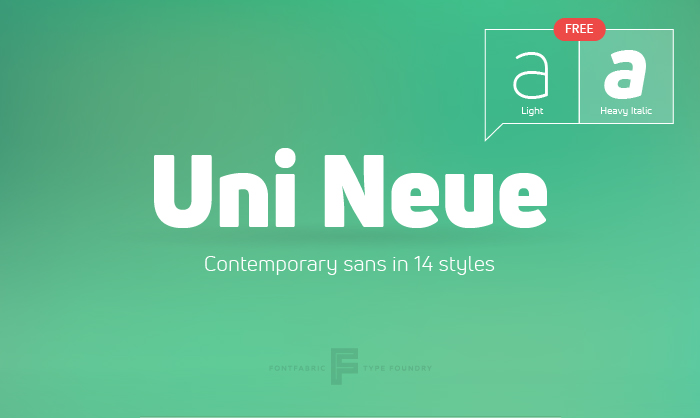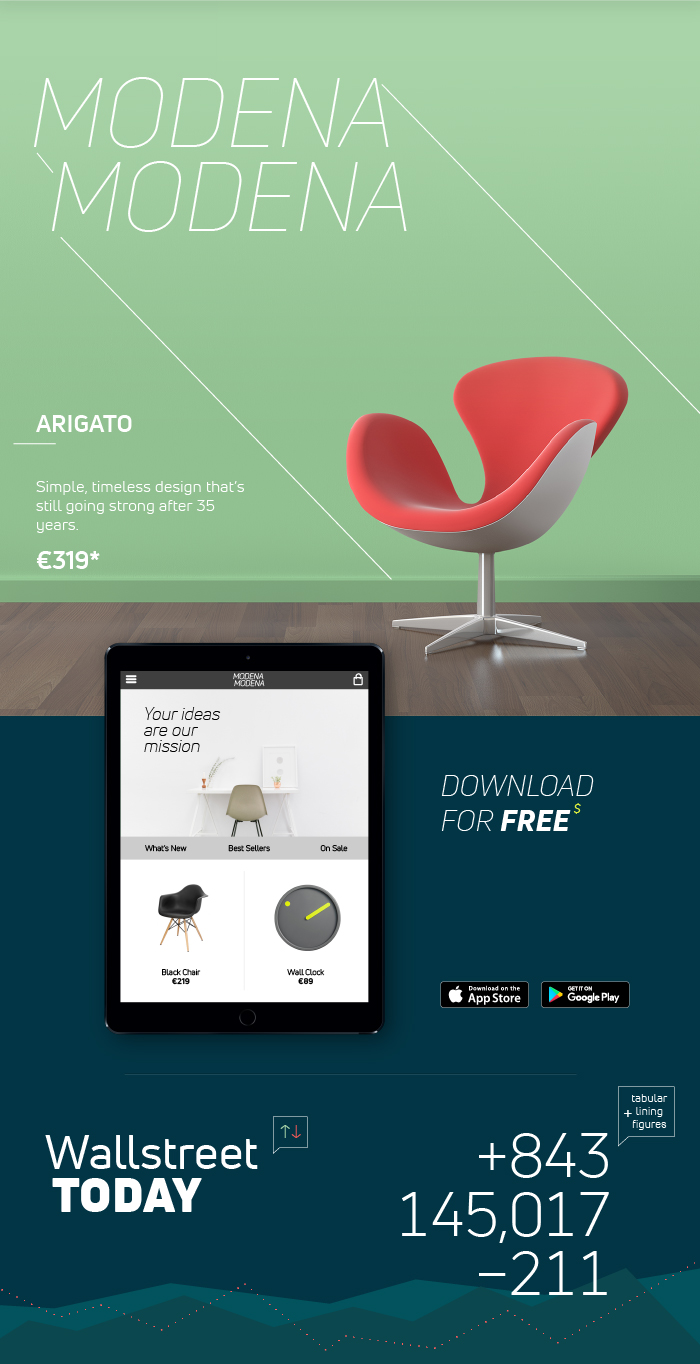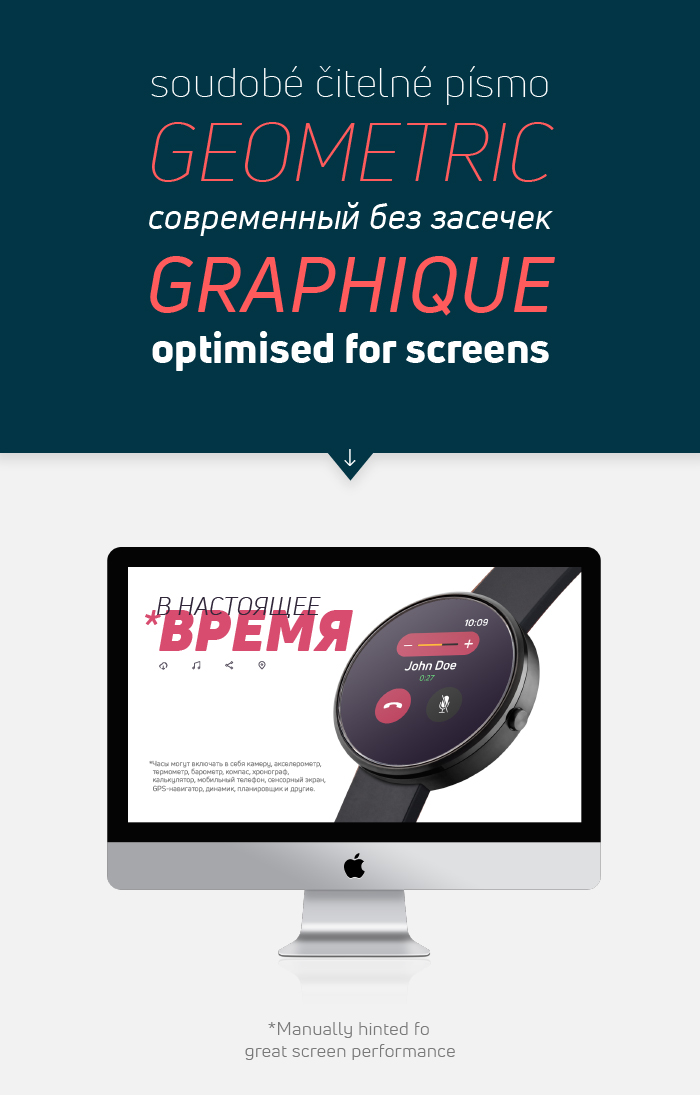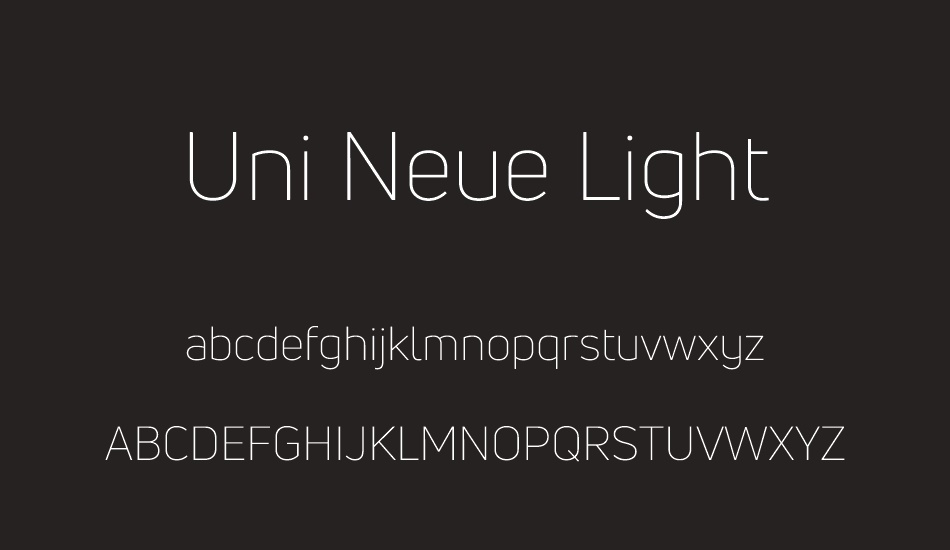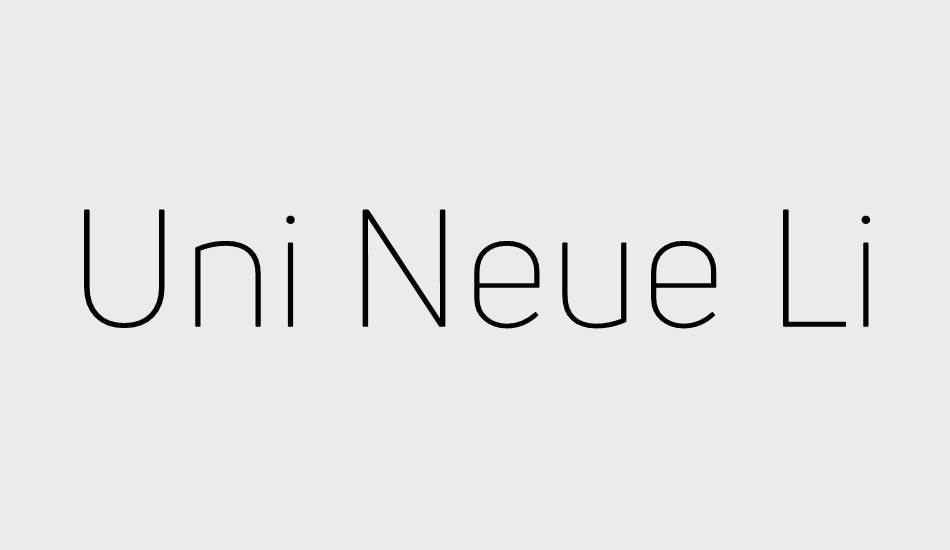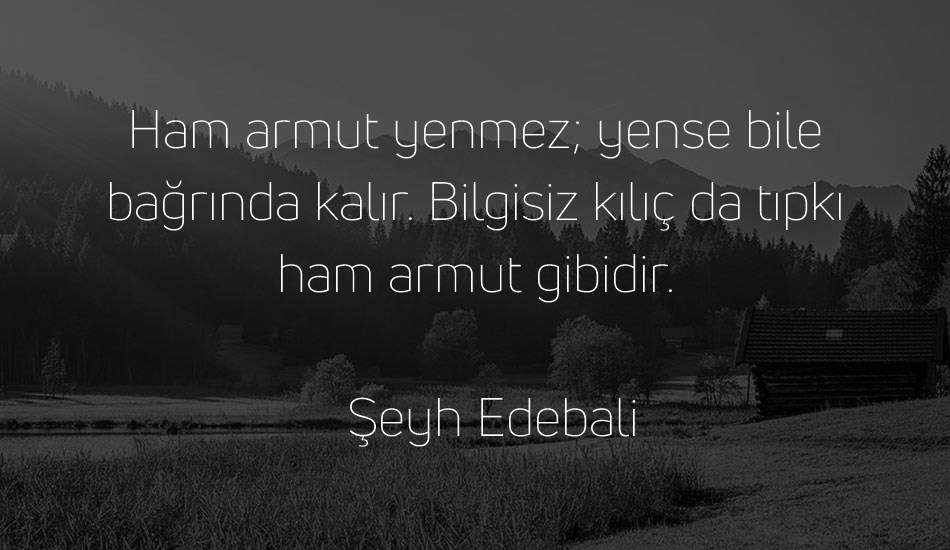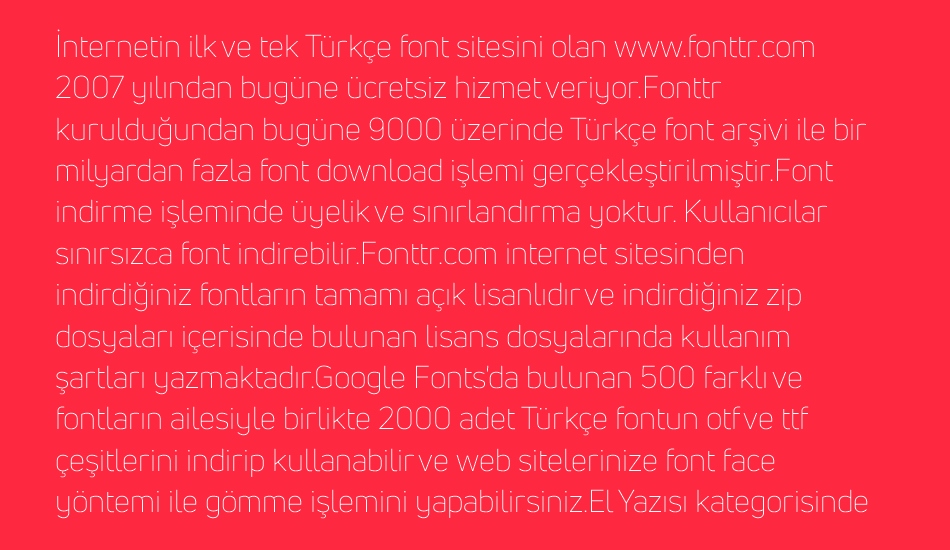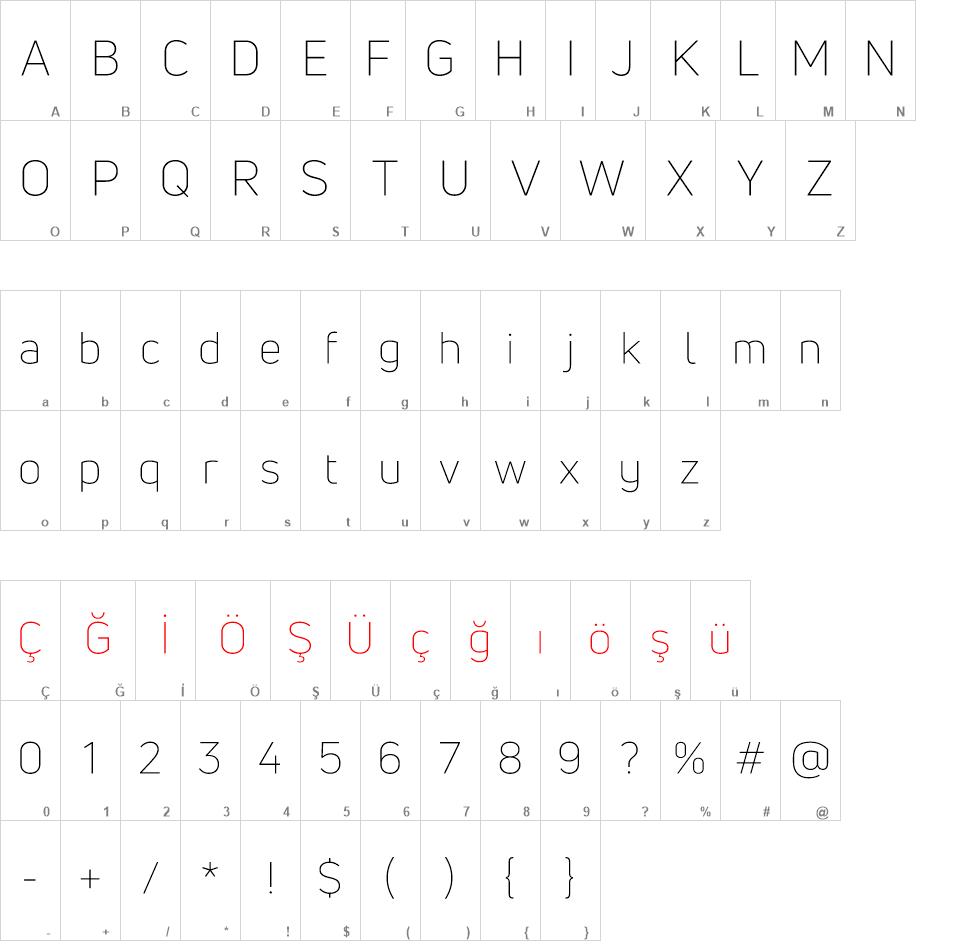
Uni Neue, Fontfabric tipi dökümhanenin en tanınmış ve en çok imza atan ailelerinden biri olan Uni Sans'ın yeni yeniden tasarlanmış versiyonudur (yeniden tasarlandı). Oranlar, genişlikler ve kalınlık (ağırlık) gibi küçük değişikliklerden büyük ayrıntılara kadar değişen bu yeni aile, yazı tipini tamamen yeni bir seviyede hissetmemizi ve anlamamızı sağlıyor.
Uni Neue font, ayırt edici bir karakter ve geometrik hissi olan modern sans serifidir. Yuvarlak köşeler yazı karakterine dostça bir görünüm verir, ancak en ciddi kurumsal kimlikleri bile markalamak için uygun profesyonel kaliteyi korur. Geliştirilmesi sırasında ödenen detaylara verilen önem bu yazı yüzünün geniş bir tasarım olanağı sunduğu anlamına gelir; kullanıcıların göze çarpan tasarımları ve gerçekten ön plana çıkan markaları yaratmalarına yardımcı olur. TV, ekran, yazı işleri ve yayıncılık, logolar, markalaşma, reklamcılık ve paketleme için mükemmeldir. Genişletilmiş Latince, Kiril ve Yunanca da dahil olmak üzere çok çeşitli dilleri destekler. Ailenin İnce'den Siyaha kadar değişen yedi ağırlıkları ve italik italikleri var. Yazı tipi, mükemmel bir web ve masaüstü performansı sağlamak için elle ima edildi.
Uni Neue Light font